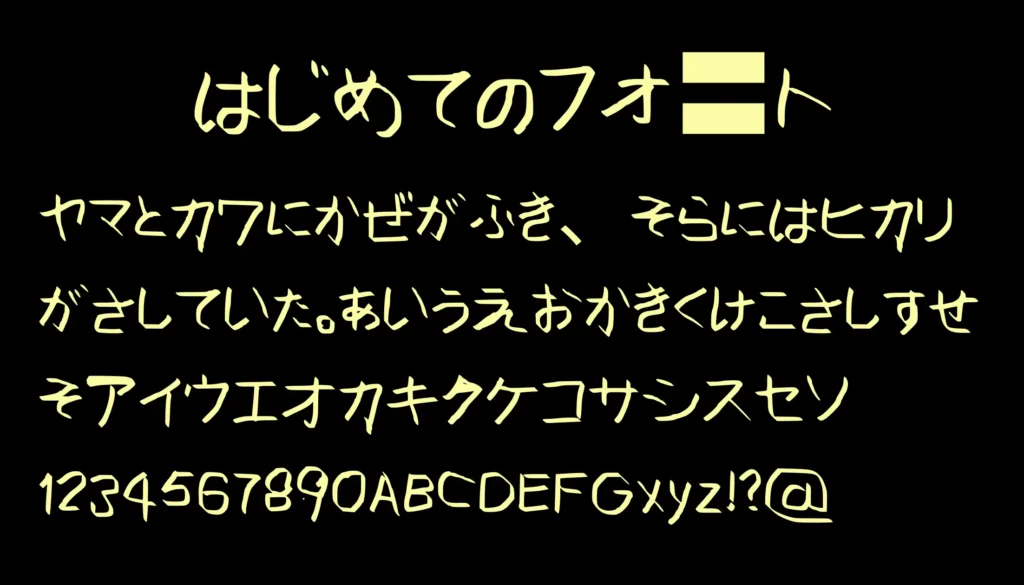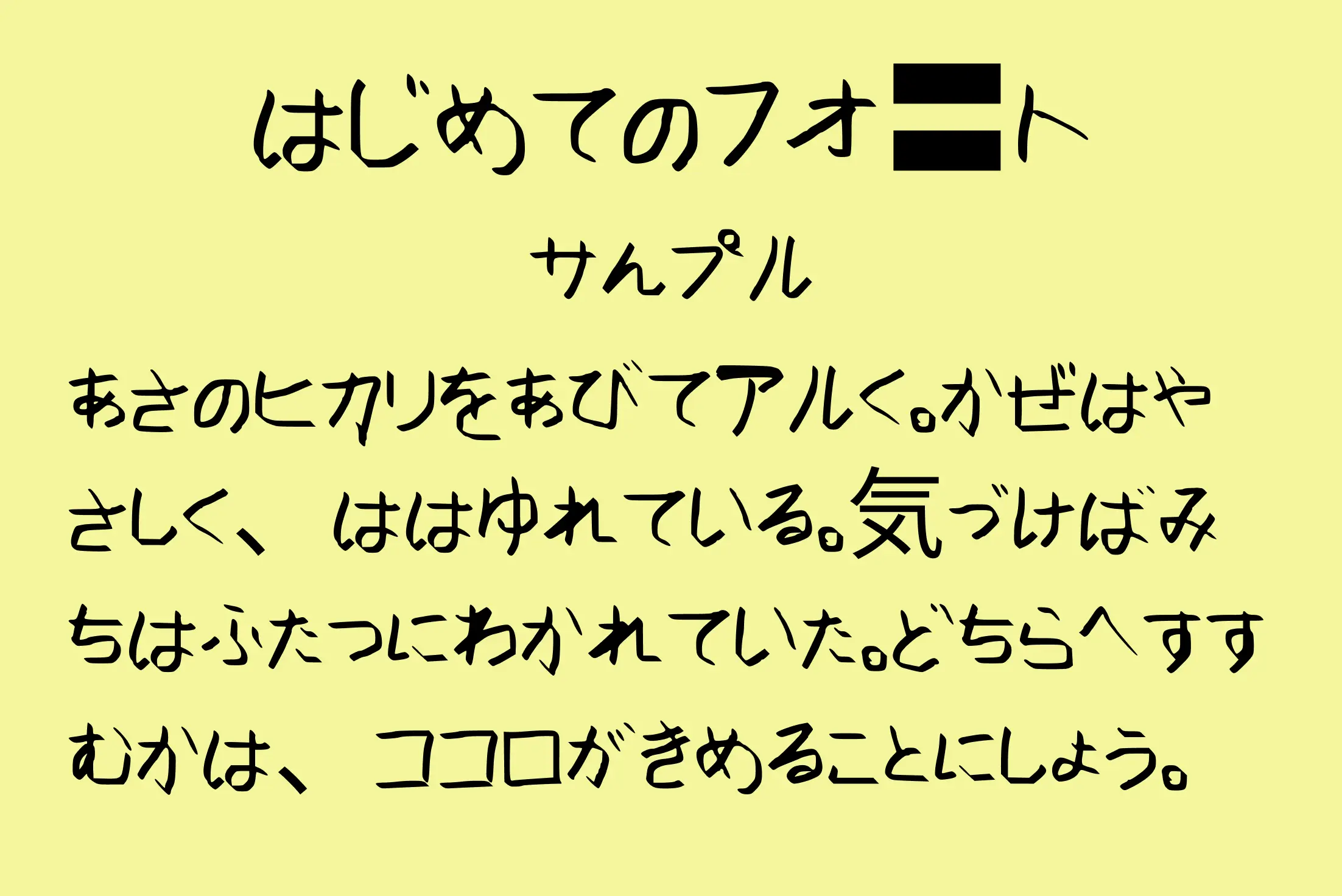
細く角張った線と不規則な字形が印象的な、手書き風のフリーフォントです。素朴でかわいらしい雰囲気の中に、少し不思議でクセのある表情を感じられます。ロゴやタイトル、動画のテロップ、SNSのアイキャッチなど、文字の個性を生かしたデザインにおすすめです。
はじめてのフォ〓ト
細く角張った線と不規則な字形が印象的な、手書き風のフリーフォントです。素朴でかわいらしい雰囲気の中に、少し不思議でクセのある表情を感じられます。ロゴやタイトル、動画のテロップ、SNSのアイキャッチなど、文字の個性を生かしたデザインにおすすめです。